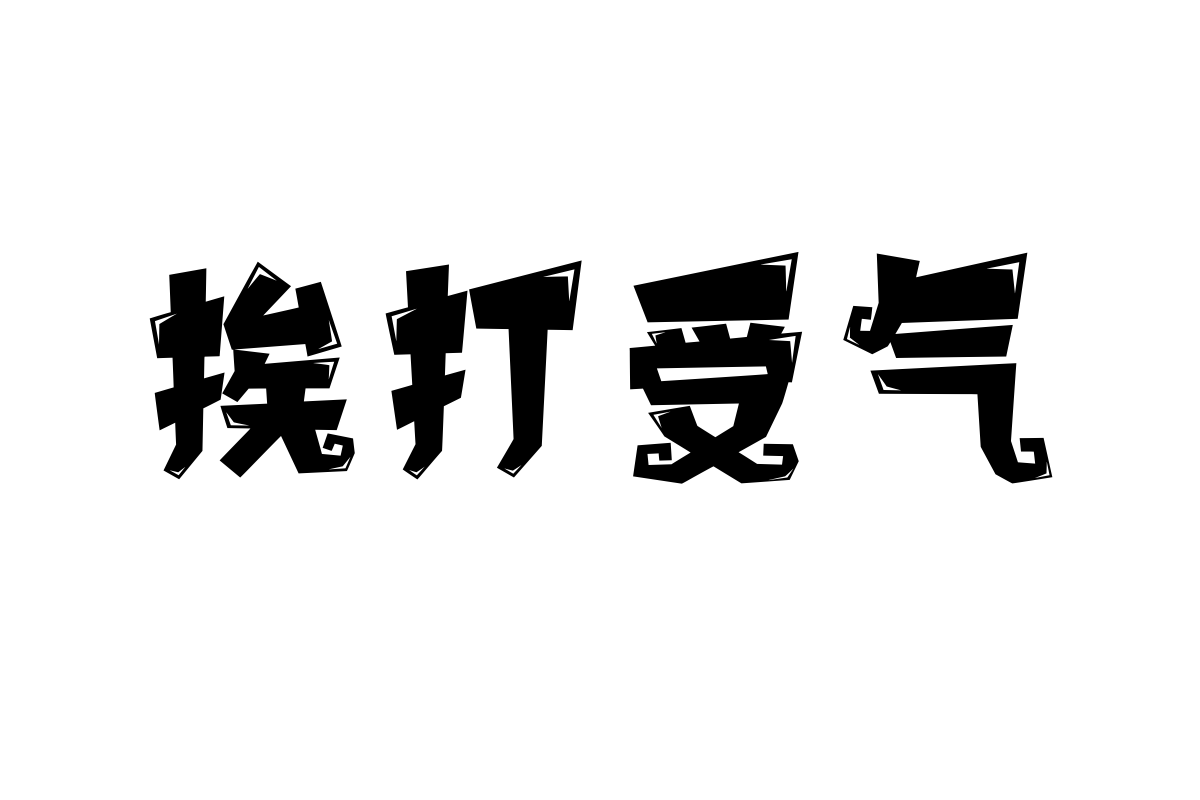
上首精灵体是一种现代的、具有未来感的字体,它结合了传统和现代的元素,创造出独特的视觉效果。这种字体的设计灵感来源于自然形态,如树木、山脉、花朵等,通过抽象化和简化的方式,将它们的形状和结构融入到字体中。
上首精灵体的笔画流畅,线条优美,既有传统的书法韵味,又不失现代的审美观。它的字形大小不一,既有大写字母的磅礴气势,又有小写字母的细腻柔美,使得整个字体充满了动感和生命力。
这种字体的特点是简洁明了,易于阅读,同时也具有很强的视觉冲击力。无论是用于标题、广告还是设计作品,上首精灵体都能展现出其独特的魅力。